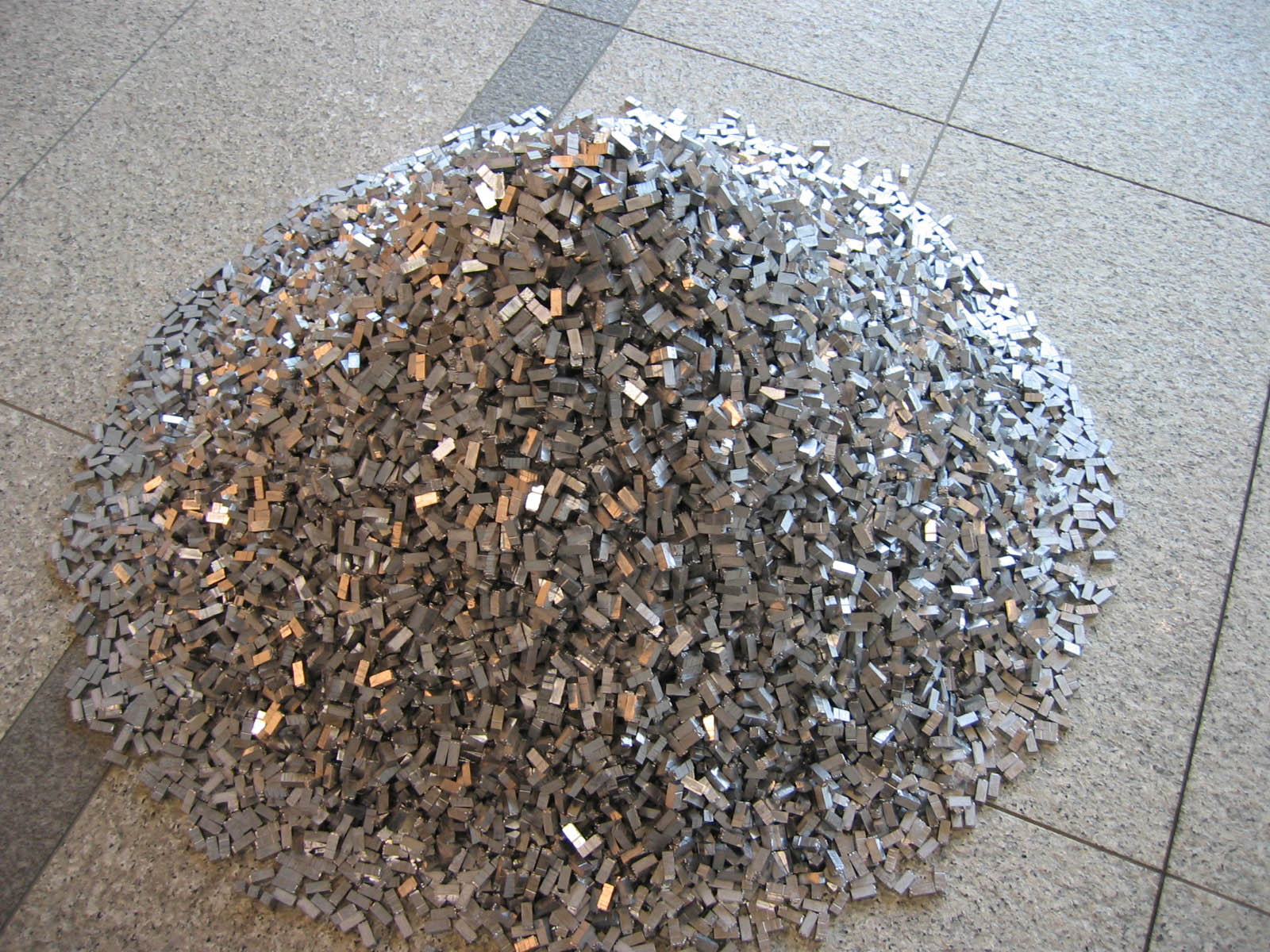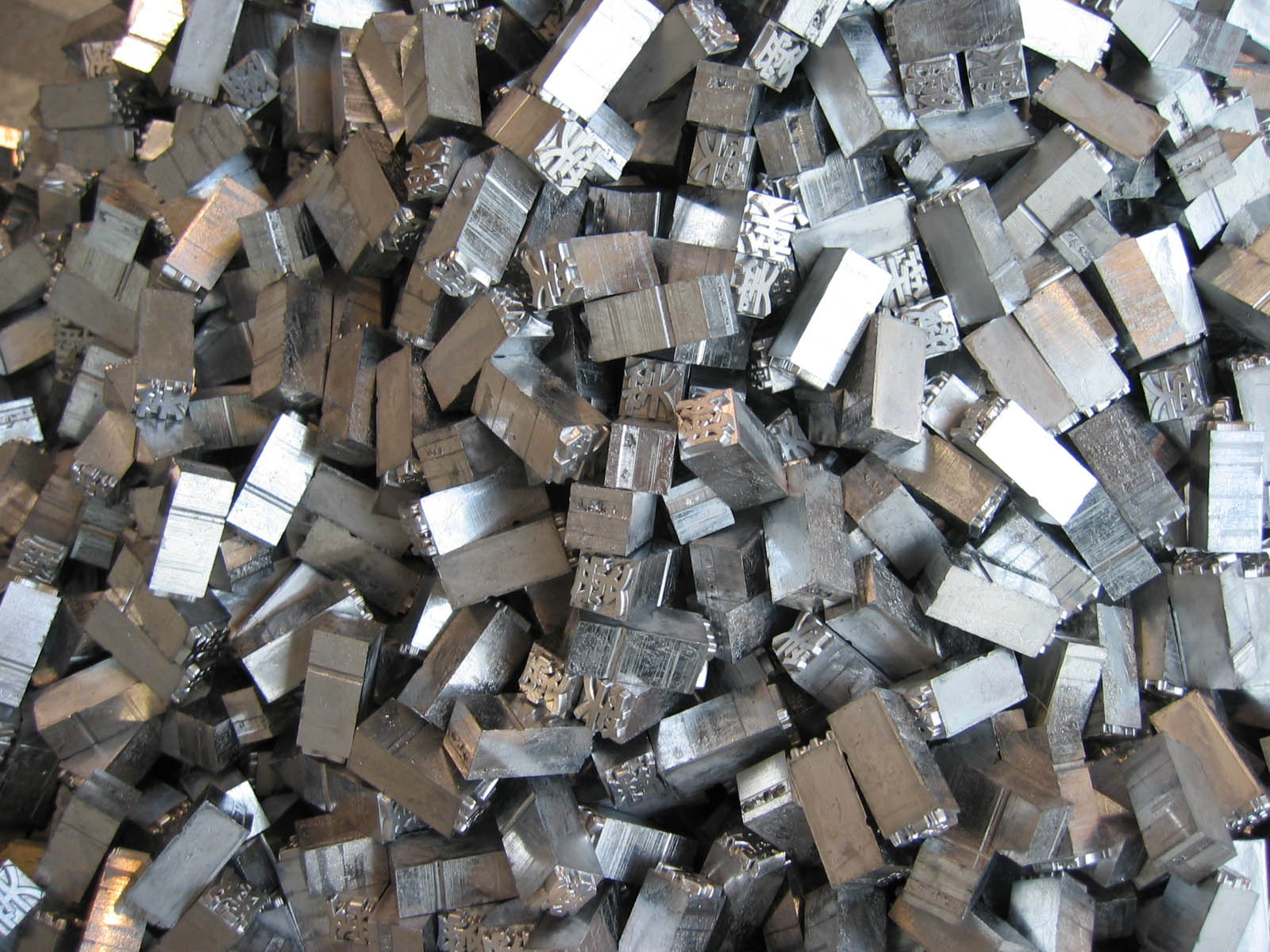
第3回 3万個の愛と笑い
作品について
イチハラヒロコ「愛と笑いの日々。」 2004年
展覧会カタログの表紙にも「愛と笑いの日々。」が使われています
東京都現代美術館で2005年1月15日(土)~3月21日(月・祝)まで開催されている企画展・motアニュアル2005「愛と孤独、そして笑い」に、現代美術家のイチハラヒロコさんが「愛と笑いの日々。」というタイトルで、金属活字を使った作品を出品しています。
イチハラさんといえば、ことばをモリサワゴシックMB101という太いゴシック体で印字したインスタレーションで知られます。「万引きするで。」と印刷されたショッピングバッグ、大阪府・布忍神社の恋みくじ、心斎橋そごう工事の仮囲いなど、実際に作品を目にしたことのある人も多いのではないでしょうか。
西向きの展示室の窓際に金属活字の作品「愛と笑いの日々。」はありました。
活字が山のように積まれています。
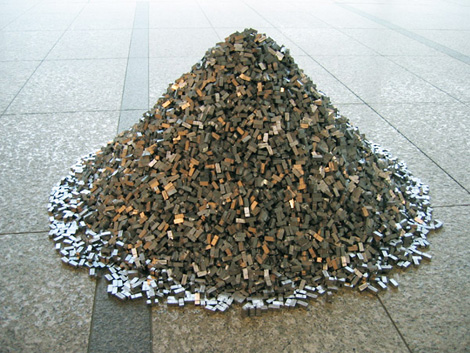
活字が積まれています
鉛色に光を反射するその山は、さほど大きくはありません。間近に寄ると、その一本一本が、「愛」「笑」という2文字が積み重ねられた山であることに気づきます。その総数は31025個にものぼります。
間近に寄るとぜんぶ「愛」と「笑」(クリックすると大きな写真が表示されます)
上から見てもぜんぶ「愛」と「笑」(クリックすると大きな写真が表示されます)
「愛と笑いの日々。」で使用された3万個の活字は、昨年、大日本印刷市谷工場にある活字鋳造機で鋳込まれました。
「愛と笑いの日々。」を鋳込んだ鋳造機
実際に活字を鋳込んだ鋳造機は小池製作所の活字鋳造機です。この鋳造機は昭和45年(1970)に導入しました。
残っていた「愛」
鋳造機のレールには、鋳込まれた「愛」の活字が何本か残っていました。
「愛と笑いの日々。」と題された31025個の活字。その1本を1日に換算すると、実に85年です。活字の山がちょうど、誰かが生まれてから亡くなるまでの「日々」のように見えました。
気軽に持ち歩く文庫本でさえ、1ページ当たり数百本、本一冊分にすると数万本の活字が必要になります。辞書に至っては、どのぐらいの活字の山になるのでしょうか。
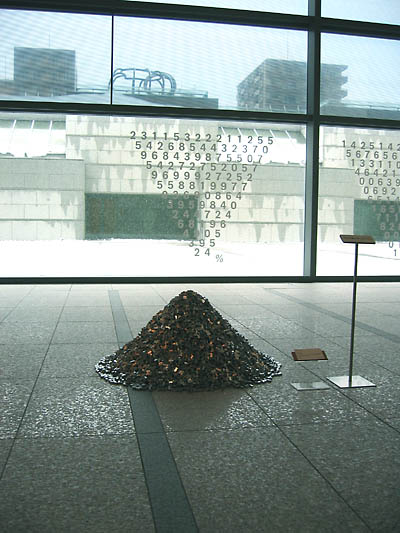
イチハラヒロコ「愛と笑いの日々。」
ちなみに、晴れた日の夕方に行くと、大きな窓から西日が射しこみ、3万個の活字がきらきらと光ってとてもきれいです。おすすめです。